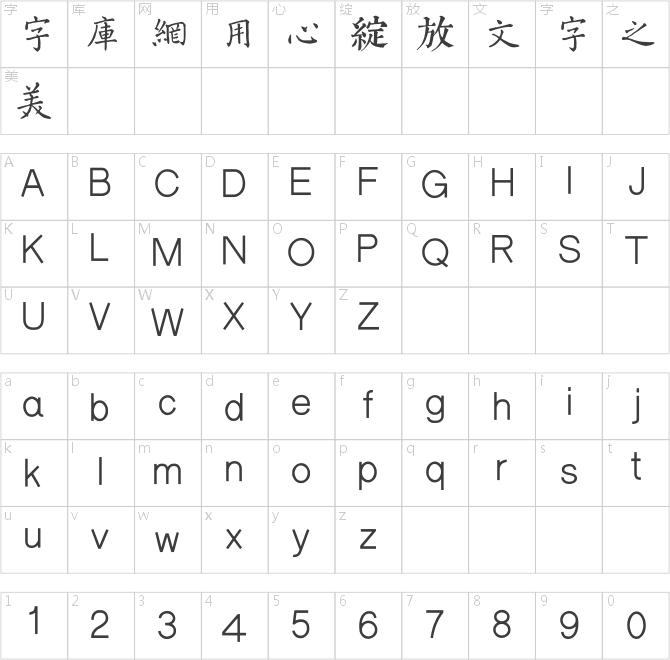
邯鄲
韓紹杰
邯鄲卷菱湖千字文字體下載邯鄲(日)卷菱湖千字文
卷菱湖(1777~1843),江戶時代後期書法家。生于越後國巷(今日本新瀉市西蒲區(qū))。原姓池田,後改姓卷,名大任,字致遠(yuǎn)、起嚴(yán),號菱湖,別號弘齋。後人稱之為右內(nèi)。
卷菱湖改變了明治維新時期政府內(nèi)御用書法家的流行體。據(jù)傳,他的學(xué)生超過萬人。與市河米庵、貫名海屋并稱“幕末三筆” 。卷菱湖幼年生長在新瀉町,那里寺院的抄經(jīng)手對他影響很大。在他19歲時,母親去世,這時的日本進(jìn)入了江戶時代。他拜畫家龜田鵬齋為師,學(xué)習(xí)詩詞、書法。他一生傾心于中國晉、唐時期書法。楷書研習(xí)歐陽詢,褚遂良。行書以李邕,王羲之為師。草書以《孝經(jīng)》、《書譜》、《十七帖》、《絕交書》為臨本。隸書則偏愛《曹全碑》。
卷菱湖在29歲時,著《十體流源》一書,并開設(shè)書院“蕭遠(yuǎn)堂”。在他53歲時,在近衛(wèi)家偶見賀知章《孝經(jīng)》,為之傾倒。他一生善詩好酒,卒于天保14年,享年67歲。